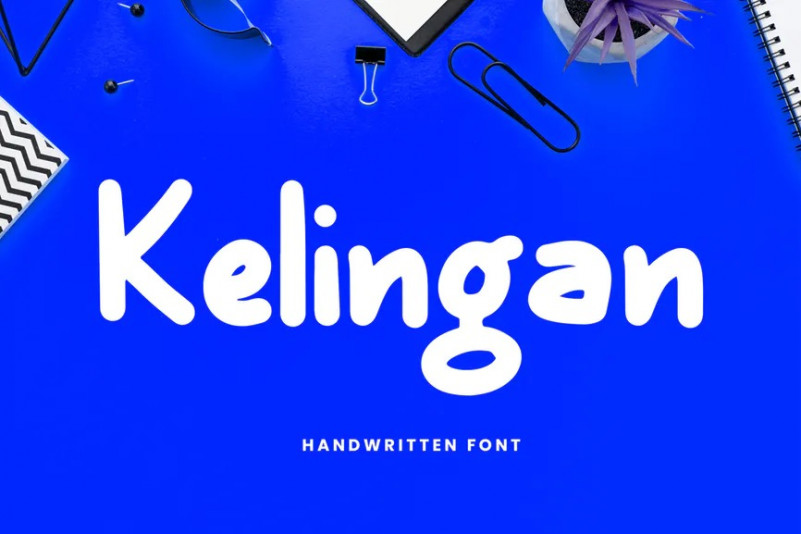
Kelingan Font
Kelingan est une police manuscrite passionnante. Il est parfait pour les projets de marque, Logo, dessins de mariage, messages sur les médias sociaux, publicités, emballage de produits, conceptions de produits, étiquettes, photographie, filigrane, invitation, papeterie et tous les projets.